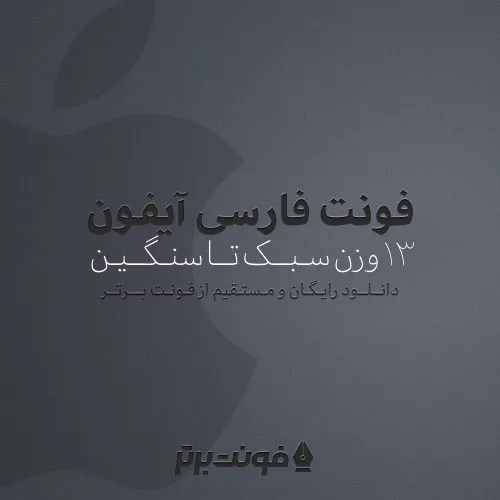
فونت فارسی اپل | فونت فارسی ایفون
فونت فارسی اپل یکی از محبوب ترین فونت های فارسی میباشد که از فونت پیشفرض اپل و گوشی های آیفون برگرفته شده است ، فونت فارسی آیفون در دیگر سایت ها به فروش می سد که شما میتوانید نسخه اصلی این فونت زیبا و حرفه ای را فقط از فونت برتر به صورت کاملا رایگان در ۱۳ وزن دانلود کنید.
فونت فارسی اپل مورد استفاده برای:
- طراحان وب سایت و گرافیست های خلاق می توانند از این فونت زیبا فونت در طراحی پروژه های تبلیغاتی و تجاری خود کمک بگیرند.